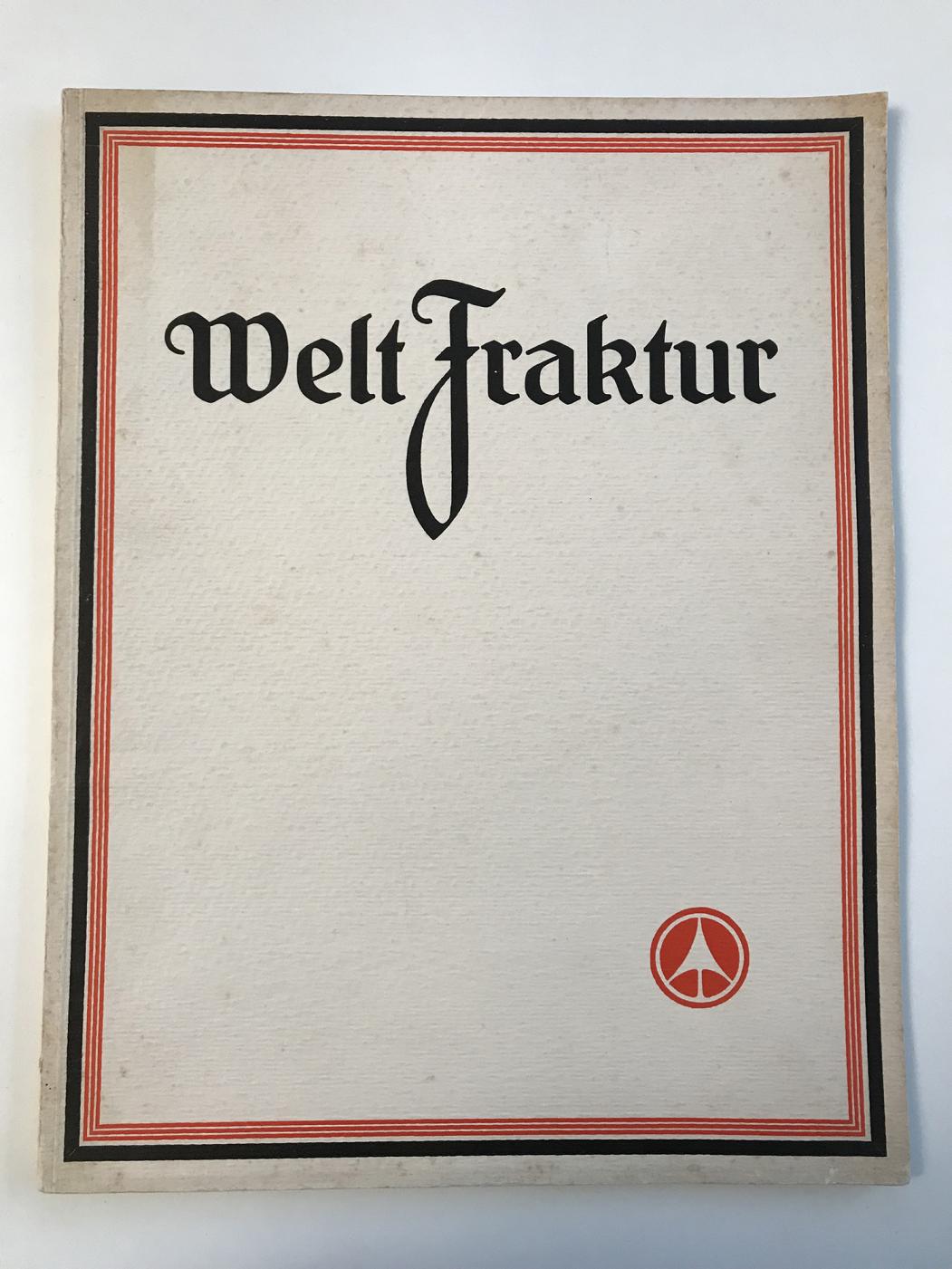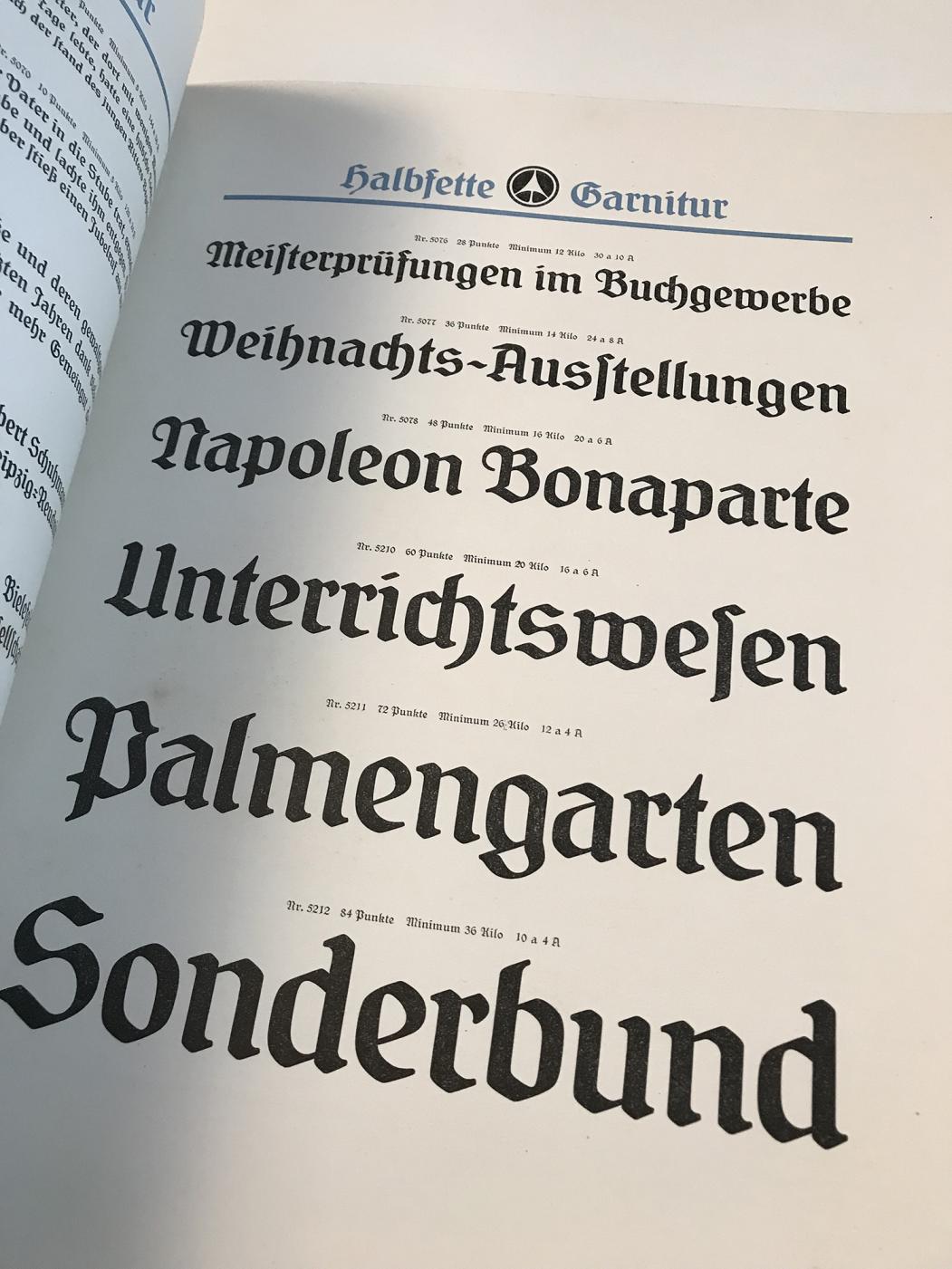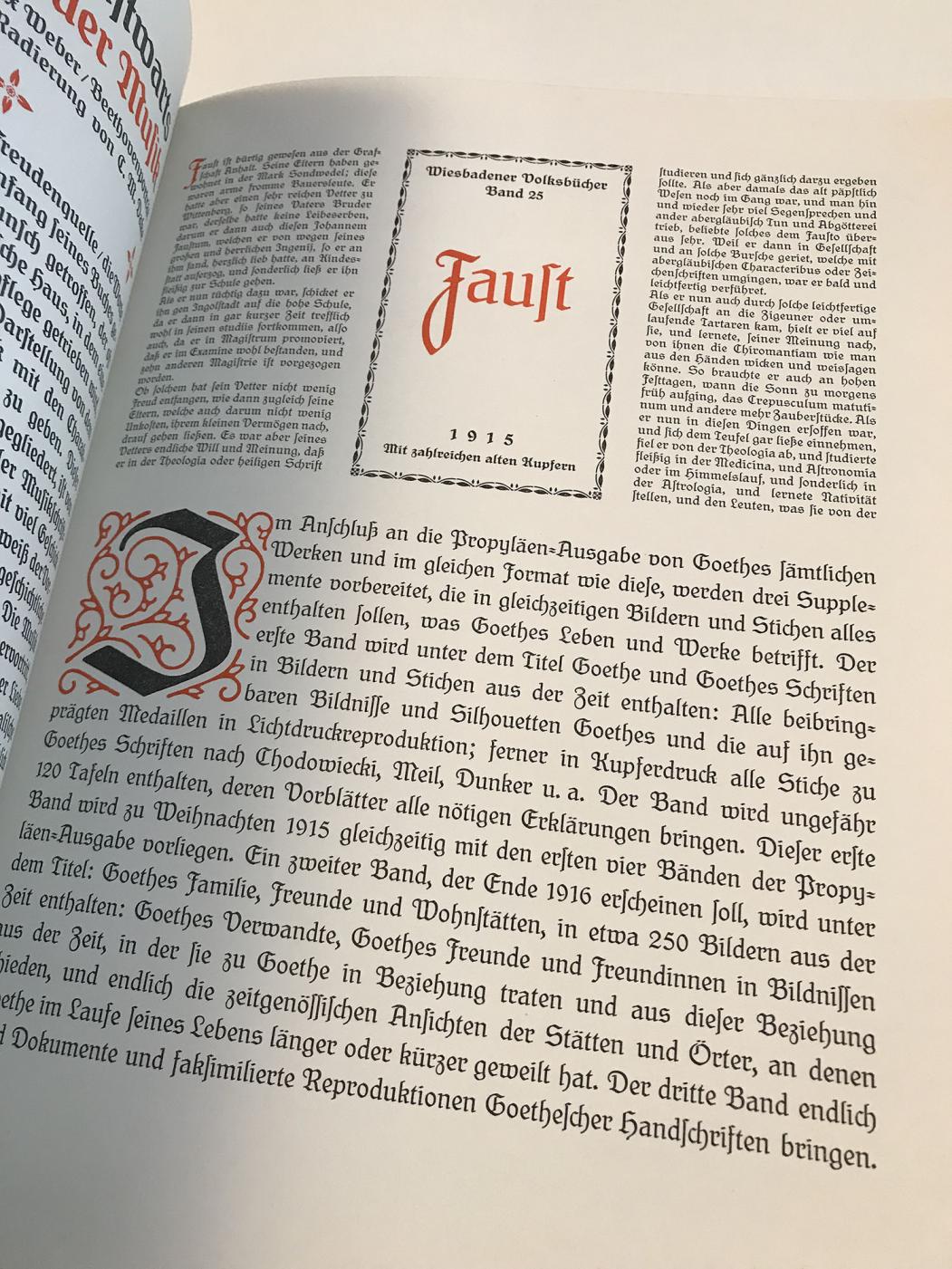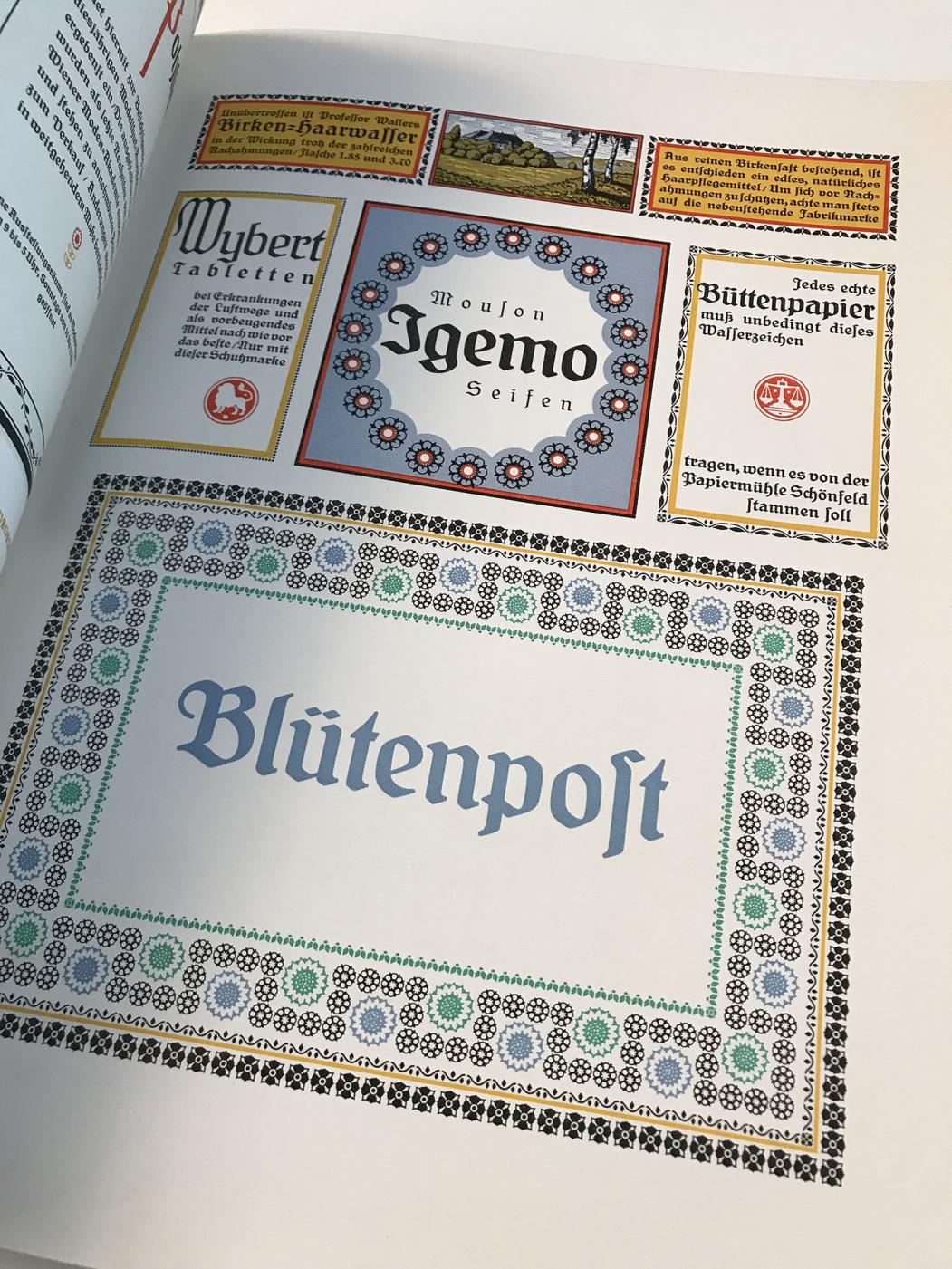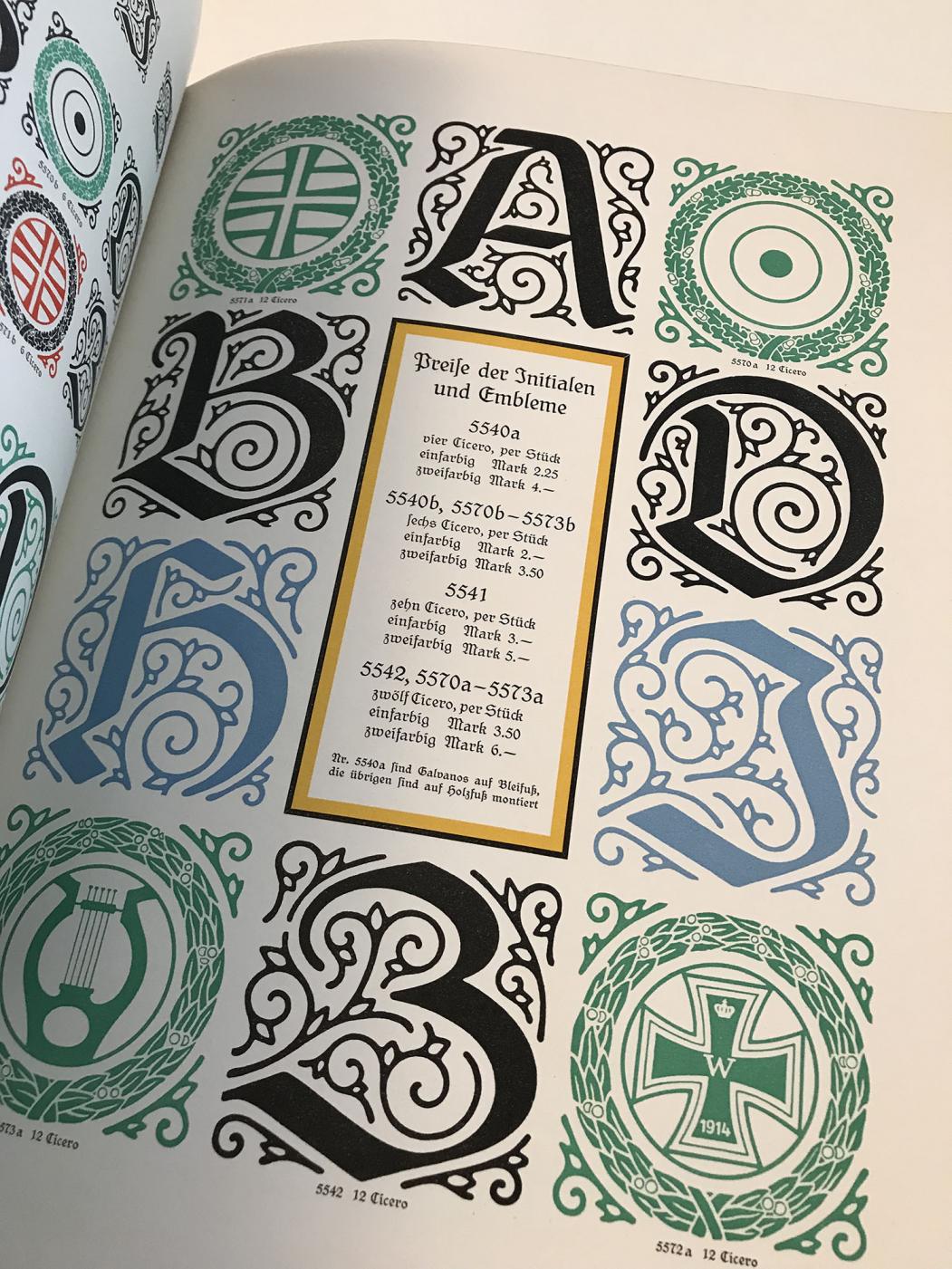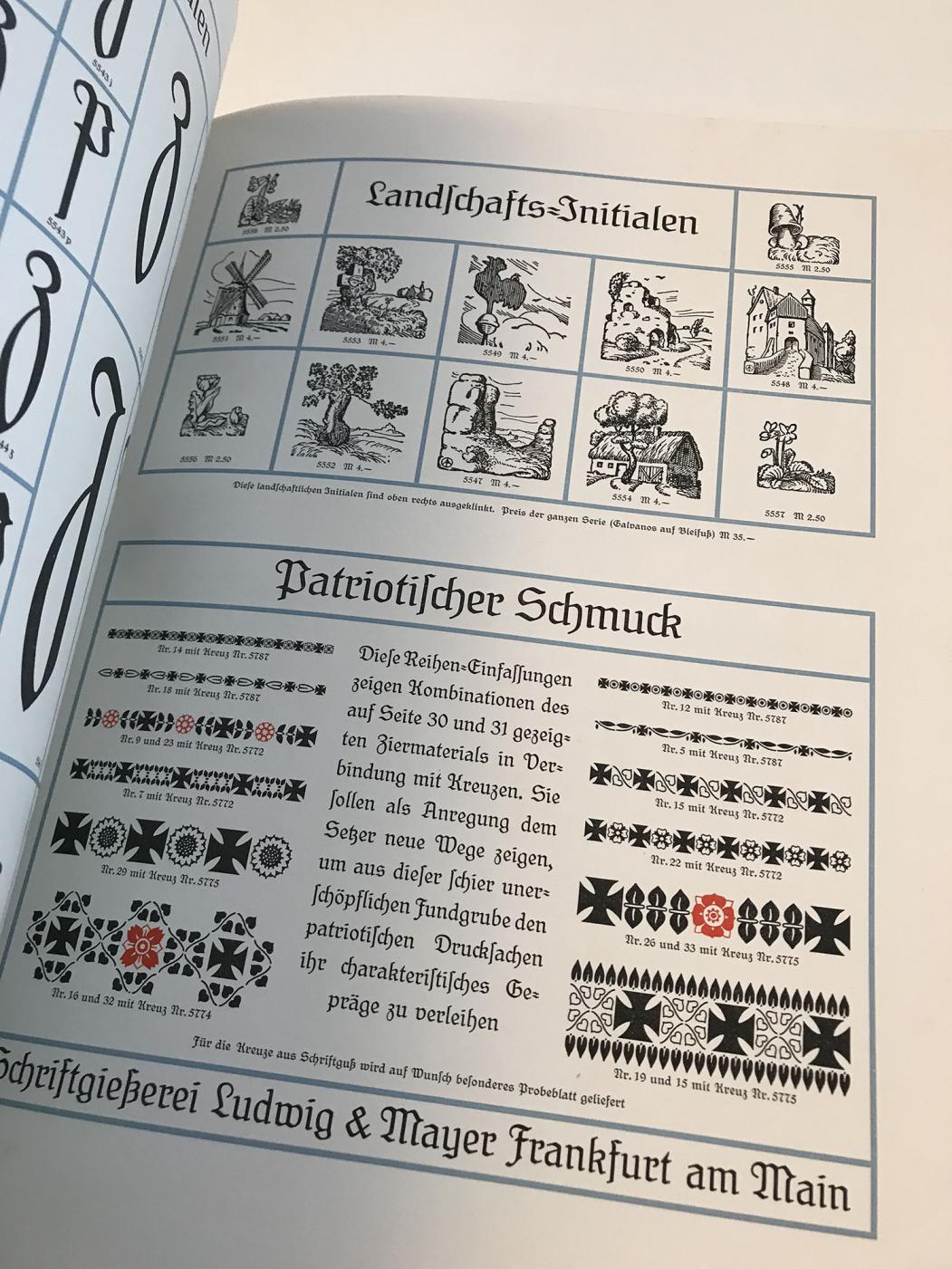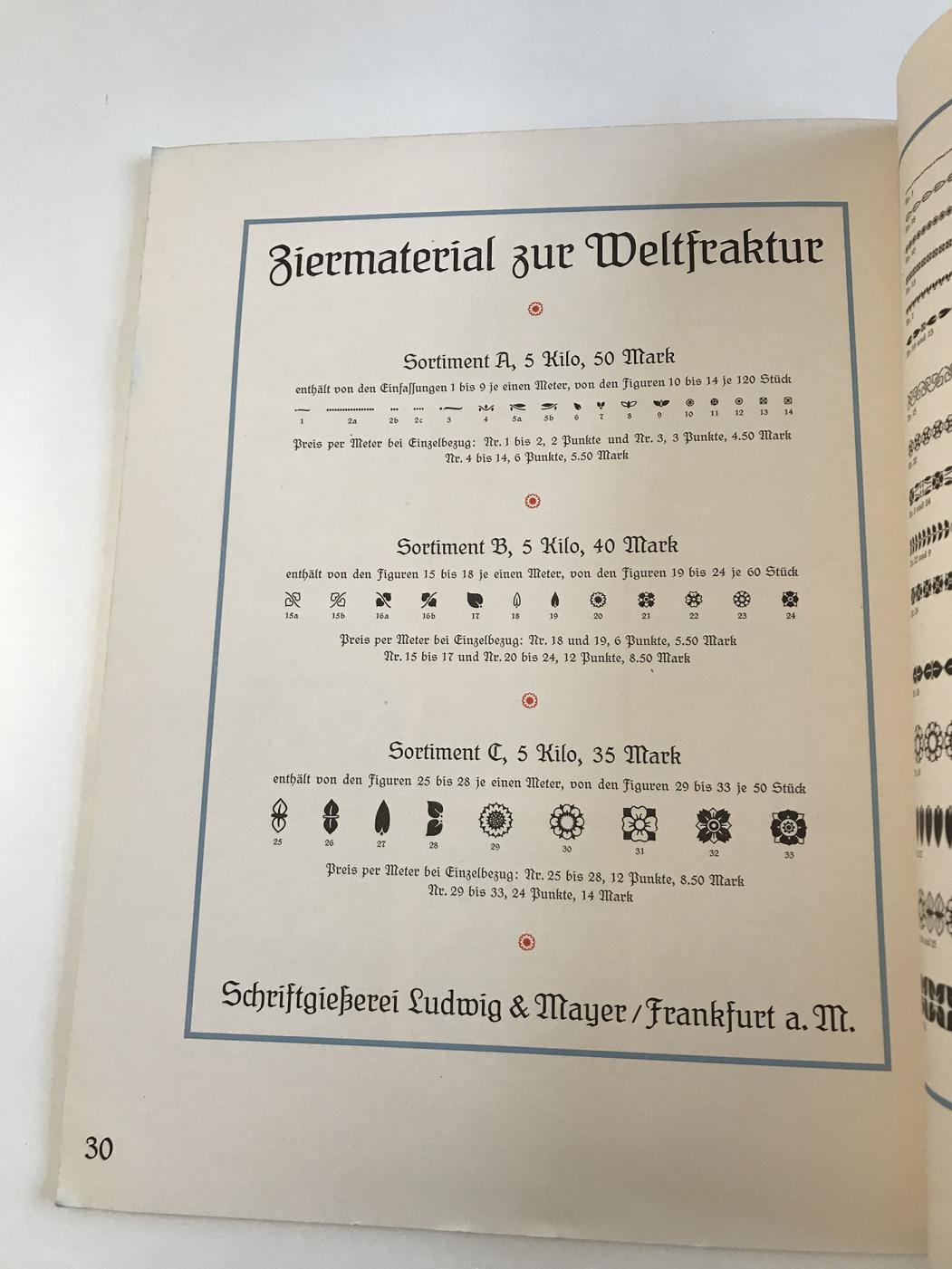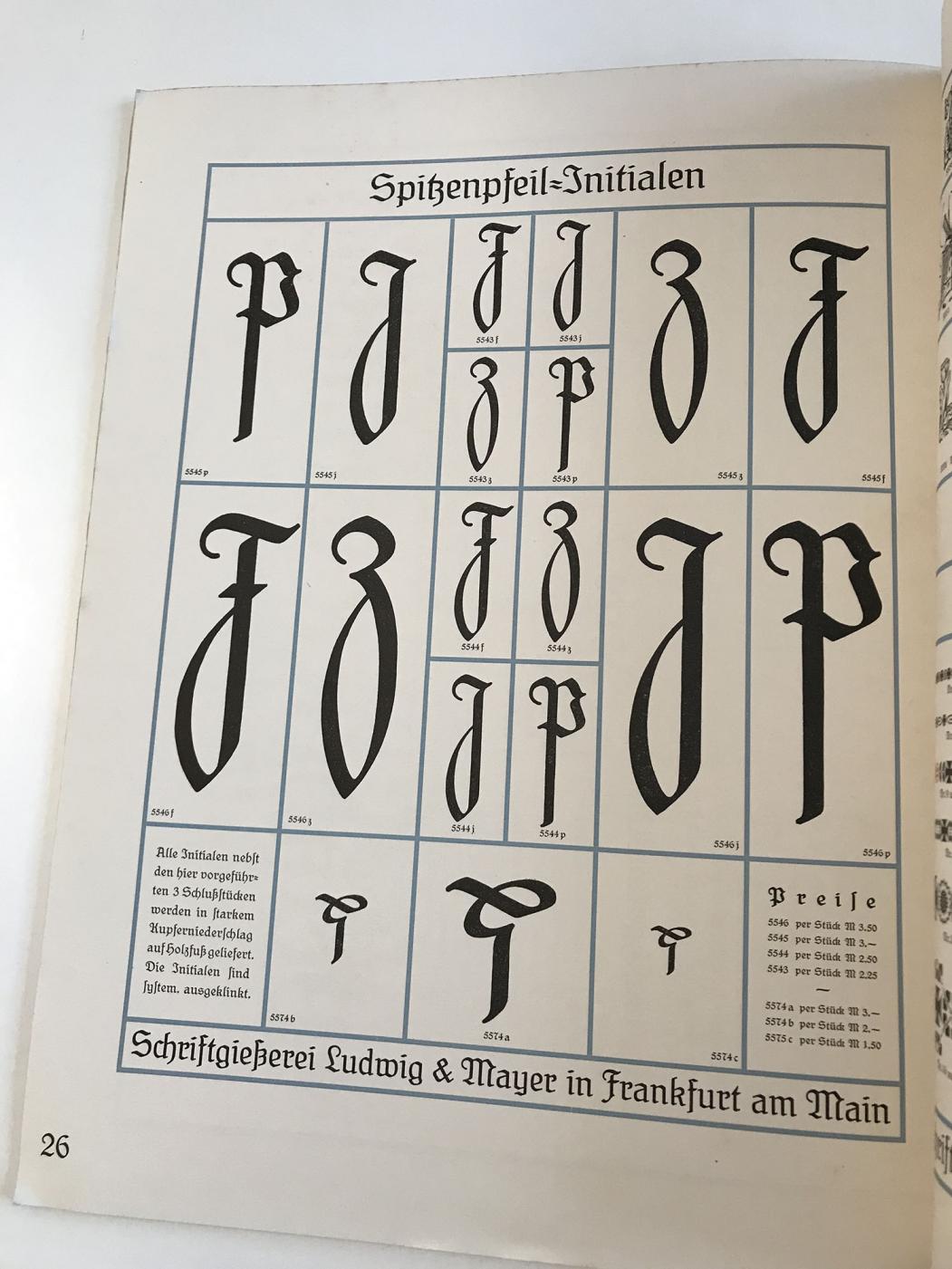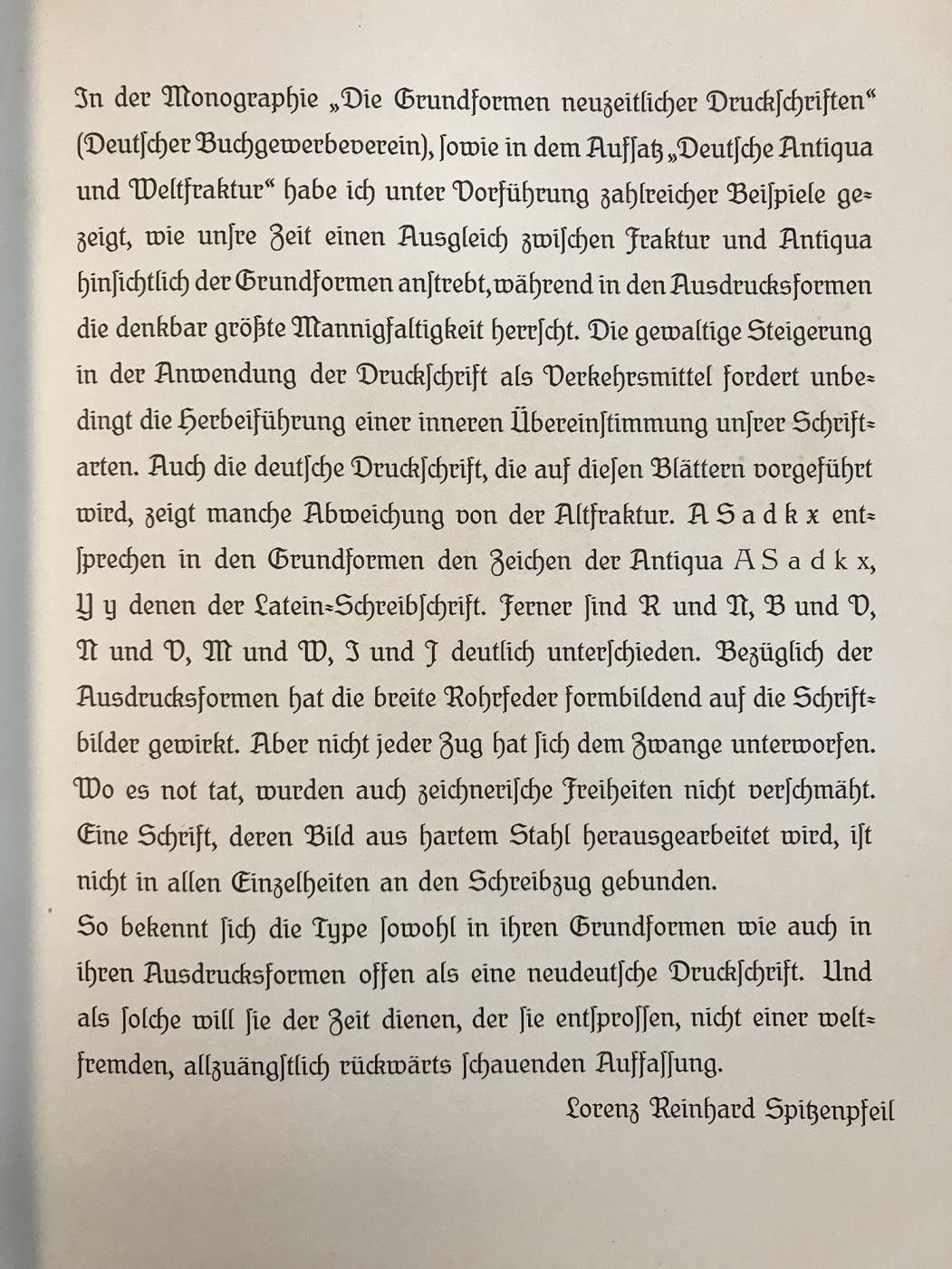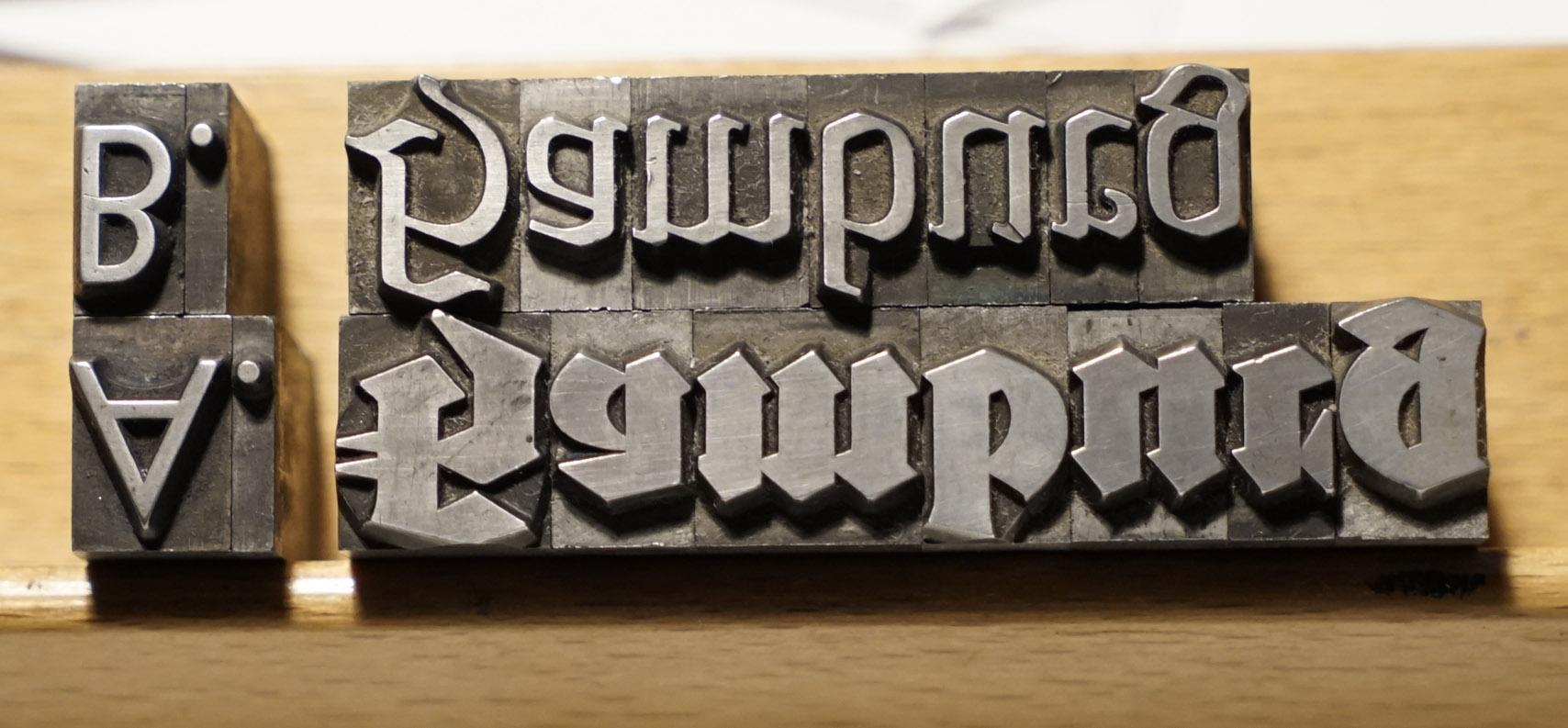
zwei unbekannte Bleisatzschriften
Bin zur Zeit dabei mir eine kleine Bleisatzwerkstatt im Keller einzurichten,
und seit heute im Besitz zweier Fraktur-Schriften. Über Schriftmuster-
Bücher, Google und was auch immer kann ich beim besten Willen nicht
herausfinden, was es ist. Einzig: A. ist jedenfalls nicht die Tannenberg. Uff!
Hallo Ralf, vielen Dank für die schnelle Antwort die mich wirklich begeistert.
Die »interessante« Weltfraktur mager habe ich nämlich in 12, 16, 24, 28 und 36 p.
Ausserdem die fette Variante in 20 und 28 p. Die Deutschmeister in  16, 28 und 36p.
Ich werde mich jetzt mal schlau machen, was die Weltfraktur so interressant
macht.
Bei der Deutschmeister bin ich mir nicht sicher, denn alles wass ich bisher
gefunden habe, hatte ein einstöckiges a und eine extrafette habe ich auch
nicht gesehen. Muss ich morgen noch mal schauen.
Ja, das verwirrt viele, weil die Gießerei unter dem Namen zwei sehr unterschiedliche Stile zusammengeführt hat. Aber es ist definitiv die Deutschmeister. Hier mit Bild http://www.klingspor-museum.de/HandbuchderSchriftarten/Handbuch_Nachtraege/Nachtrag1927.pdf
Über die gleiche Schrift(verwirrung) sind wir ja schonmal gestolpert. 😃